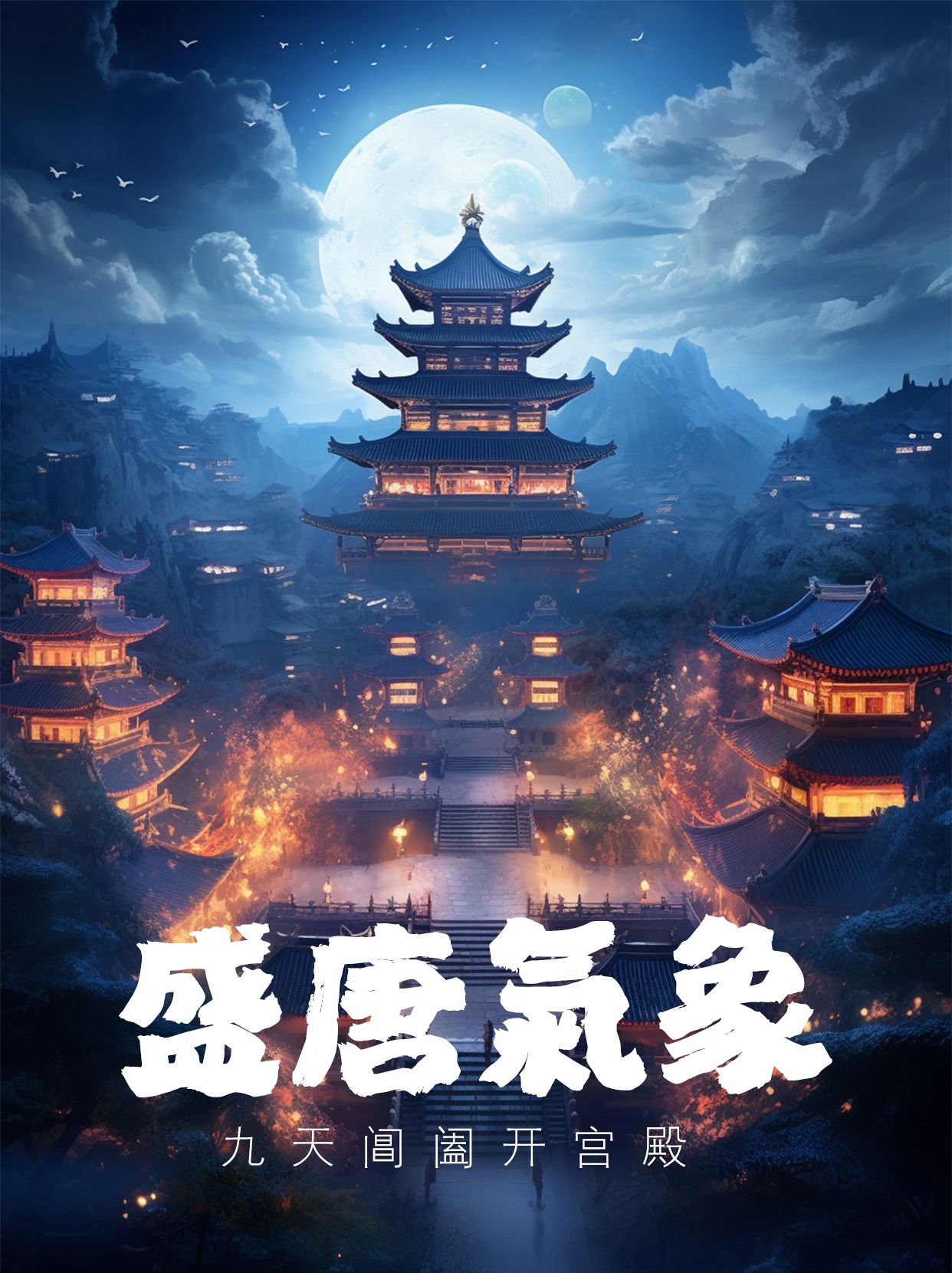
书法字体|霸气国风的书法字库——造字侠,国潮场景还得选它!
国风的潮流带来的一股文化风潮,使书法字体也重新从小众变为时代潮流。确实,书法字体向来以其古朴苍劲、雄浑有力而深受欢迎,它在凸显设计感、塑造画面冲击力、吸引用户眼球方面都具有很大优势。
励字造梦共创字库,旗下造字侠品牌,以书法字体为主,潇洒不羁、气势磅礴,将奇妙的灵感交锋、夸张的个性表达,融合在一笔一划中,打造设计师专属IP,让人人都可以成为造字侠。精选3款创意的书法字体,匹配各种国风场景~
造字侠伏魔简繁 传神,笔墨浓厚,粗细对比较为明显,字体结构较为中正,字体里笔画的“勾、提、挑、捺”等笔画特点明显、夸张,极具视觉冲击力,单字结构收放自如。
造字侠仗剑简繁 传神,一款字形稳重、笔画张扬的书法字体。折、提、钩等部首干净利落、高度折叠,颇有豪侠仗剑江湖的潇洒之感。
造字侠磅礴简繁,字体中正感官丰富,运笔富有节奏感,呈一波三折之态,笔画粗细变化明显,略有飞白,转折方圆相结合。